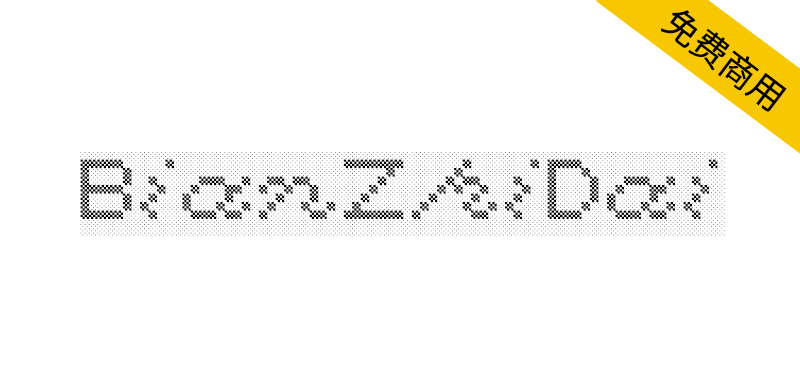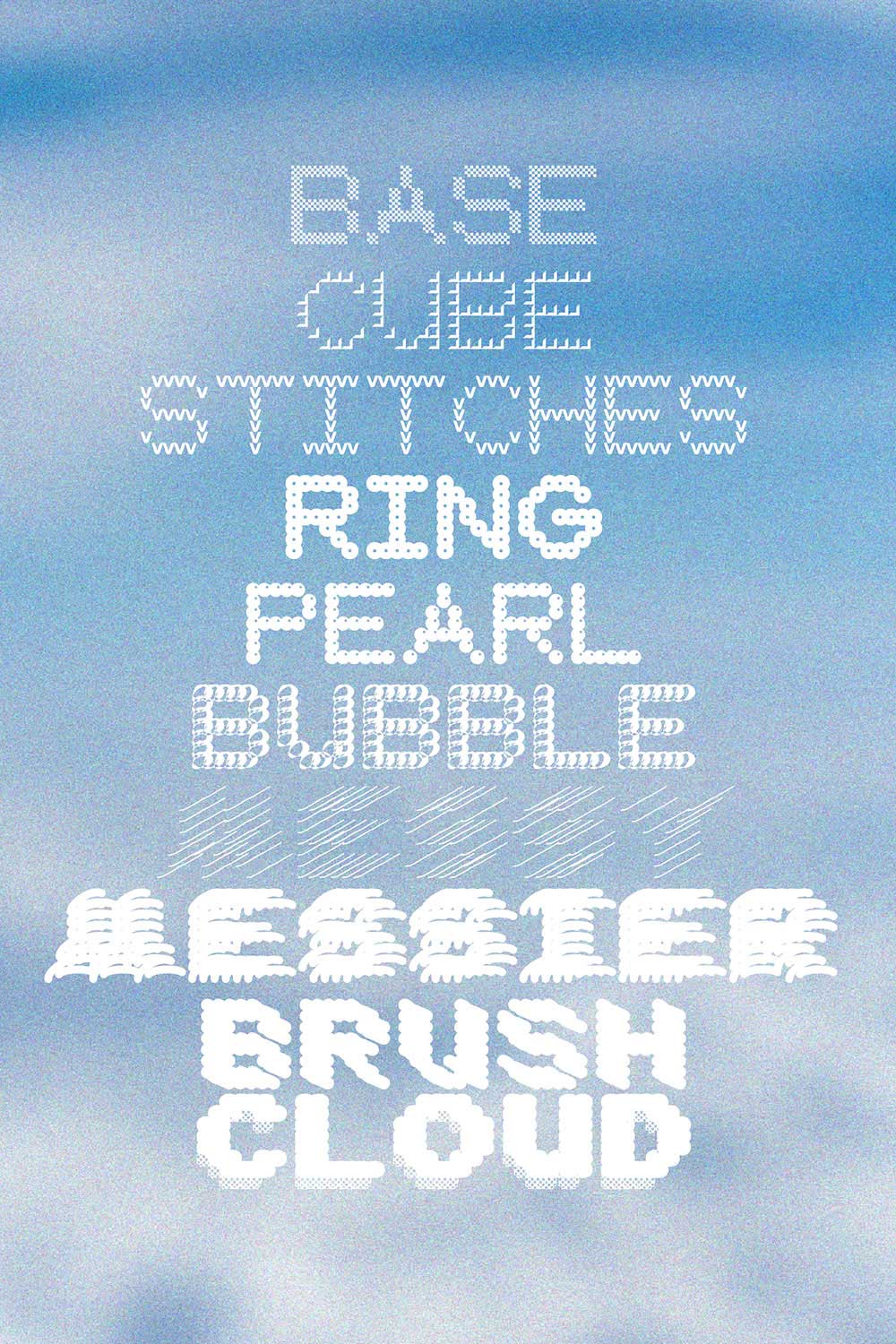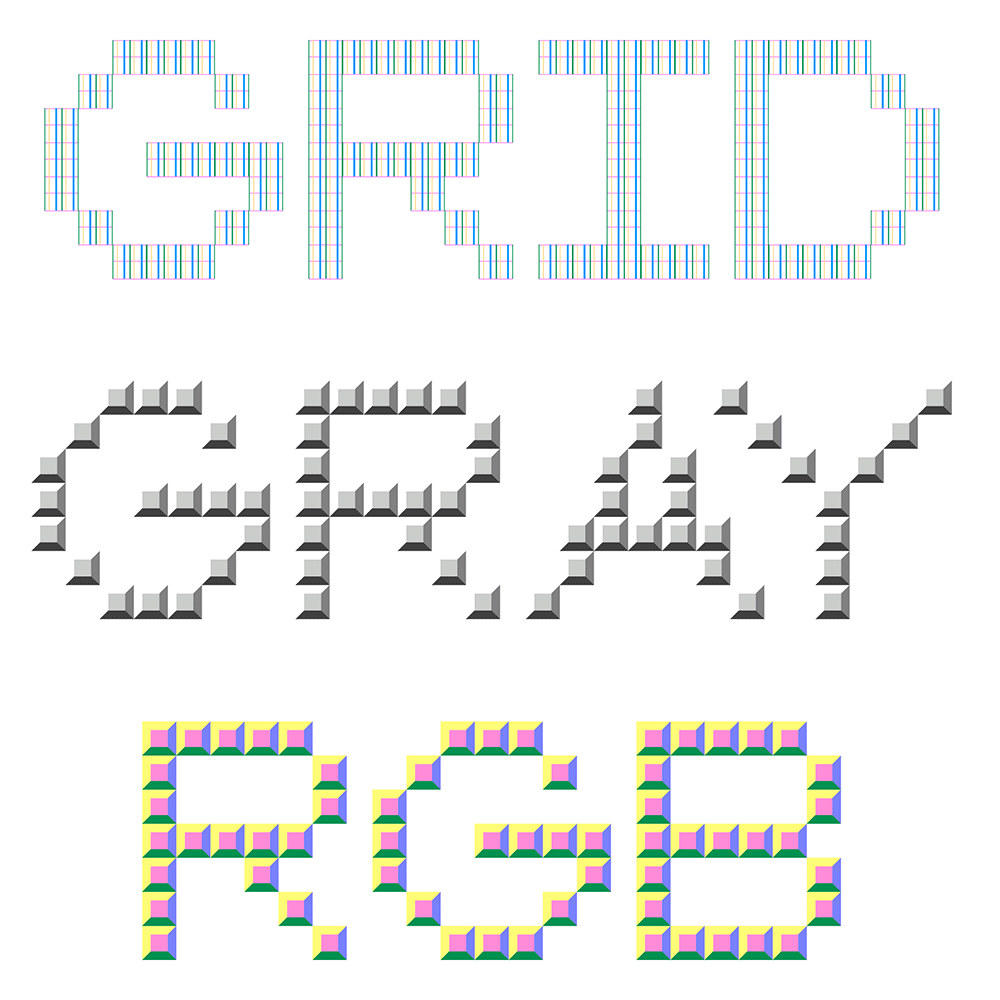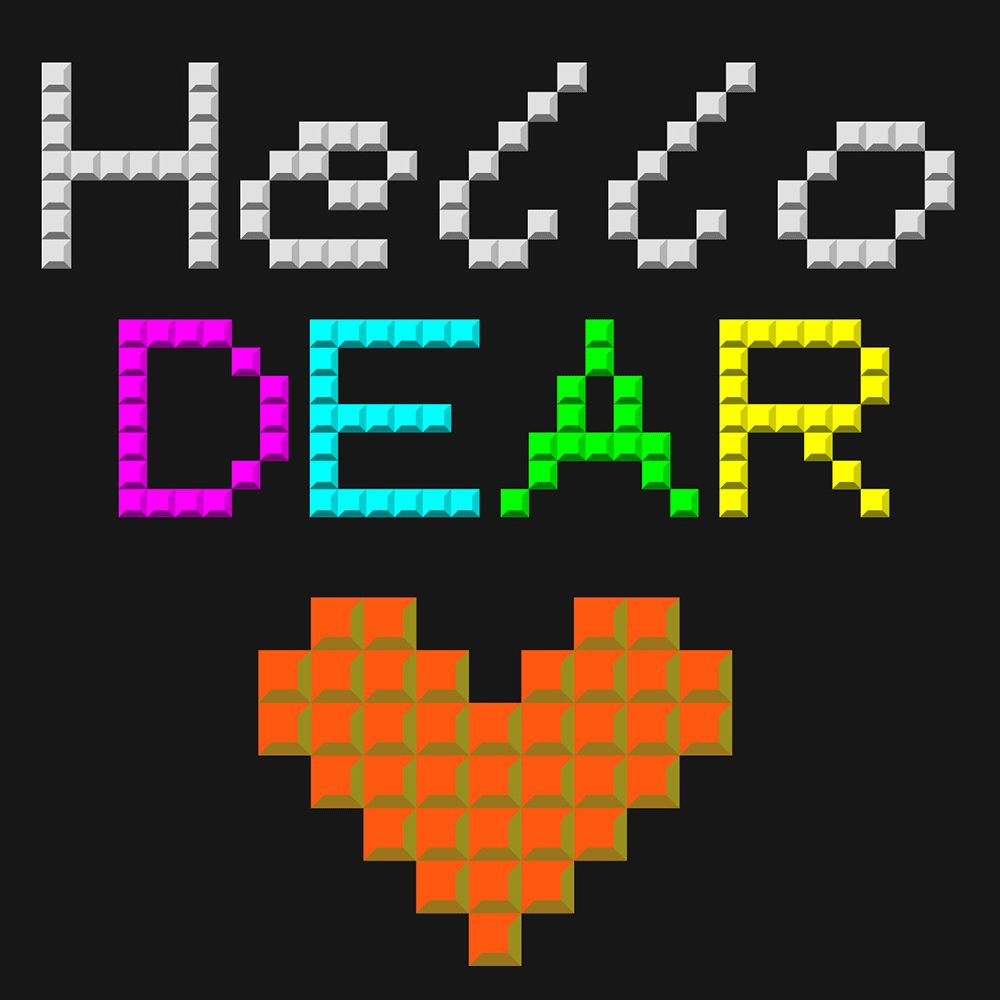
BianZhiDai的灵感来自ASCII艺术中的阴影字符和中国编织塑料袋。以前在GDC(glyphdrawingclub,由@hlotvonen和@i-tu制作的在线绘图工具)中构建,在进行修订时变成了模块化。
bianzhidai擅长色彩搭配,尤其是与不同的填充/笔划颜色相结合。试试看,玩一下。此外,整个字体是基于模块的,所以你可以用任何你喜欢的方式在Glyphs中自定义它。
bianzhidai2.0是一个更新版本,旨在为角色提供一个稳定的(ier)结构,更多的装饰/俏皮风格和(略微)增强的可读性。有十种风格:底座、立方体、缝线、戒指、珍珠、泡泡、凌乱、凌乱、画笔和云(哦,名单很长……),分层彩色字体还有另外4种样式:背面、侧面、前方和背光。
bianzhidai is inspired by shading characters in ASCII art and 编 织 袋 Biān Zhī Daì (woven plastic bag in Simple Chinese). Previously constructed in GDC (glyphdrawingclub, an online drawing tool made by @hlotvonen and @i-tu ), turned into modular when doing the revision.
bianzhidai is good with colors, especially in combination with different fill/stroke colors. Try it, and play it. Besides, the whole font is modular based, so you can customize it in Glyphs any way you like.
bianzhidai 2.0 is an updated version, which is intended to provide a stead(ier) structure for the characters, more decorative/playful styles and (slightly) enhanced readbility. With ten styles: Base, Cube, Stitches, Ring, Pearl, Bubble, Messy, Messier, Brush, and Cloud. (Hooo, long list...) There is an additional 4 styles for a layered color font: bianzhidai_COLR back, side, front and hightlight.